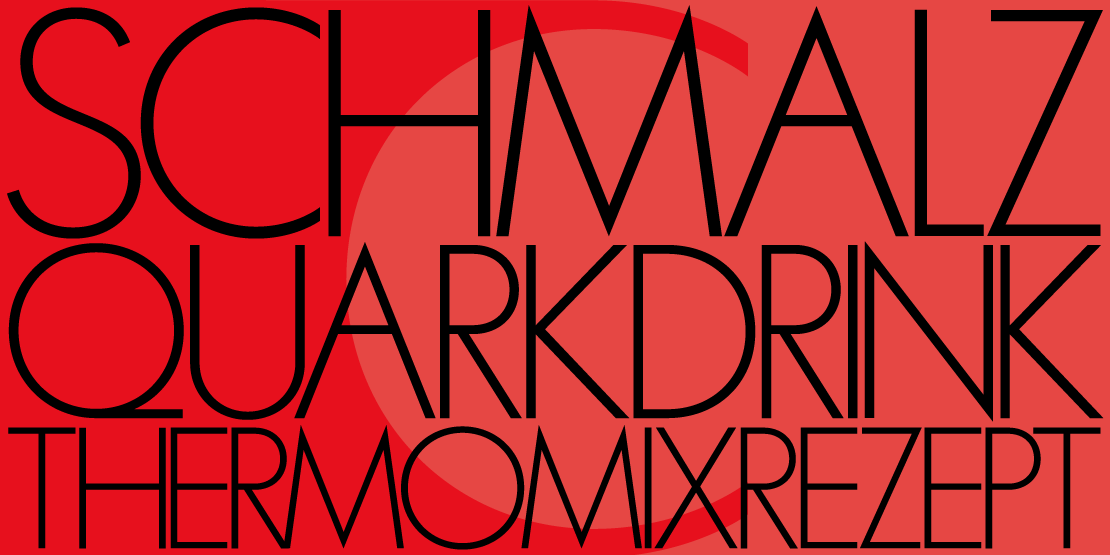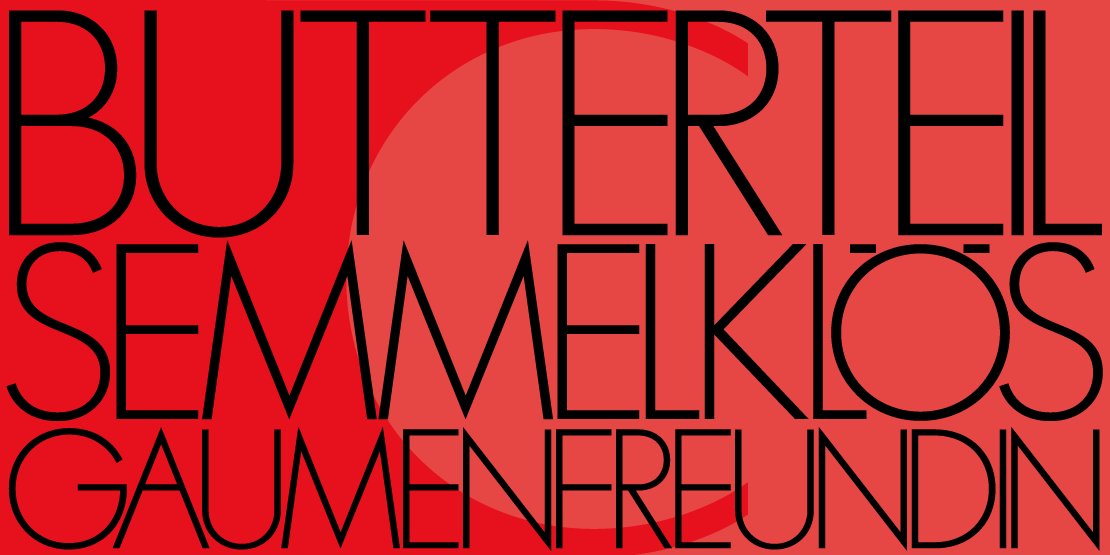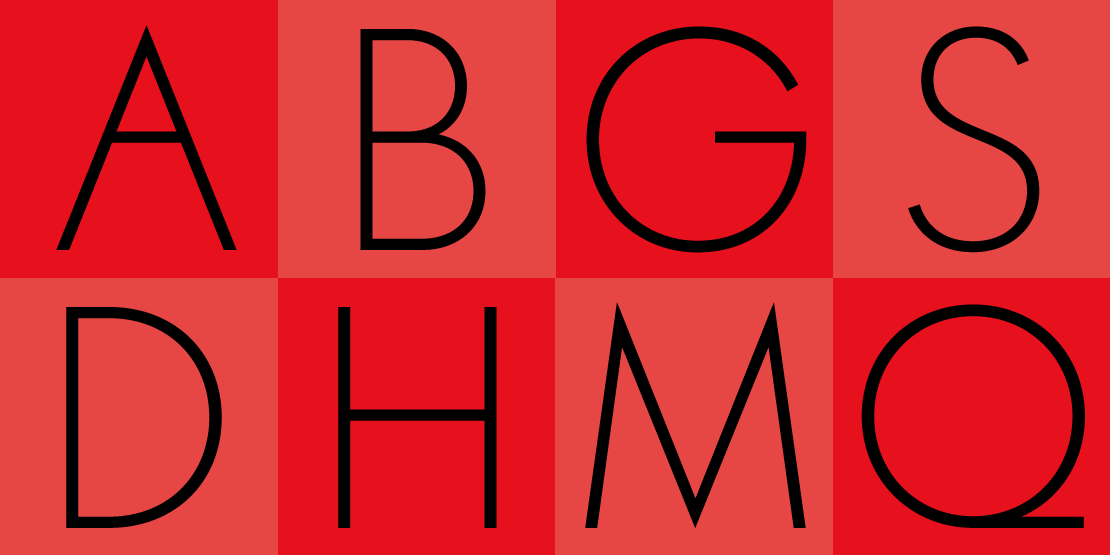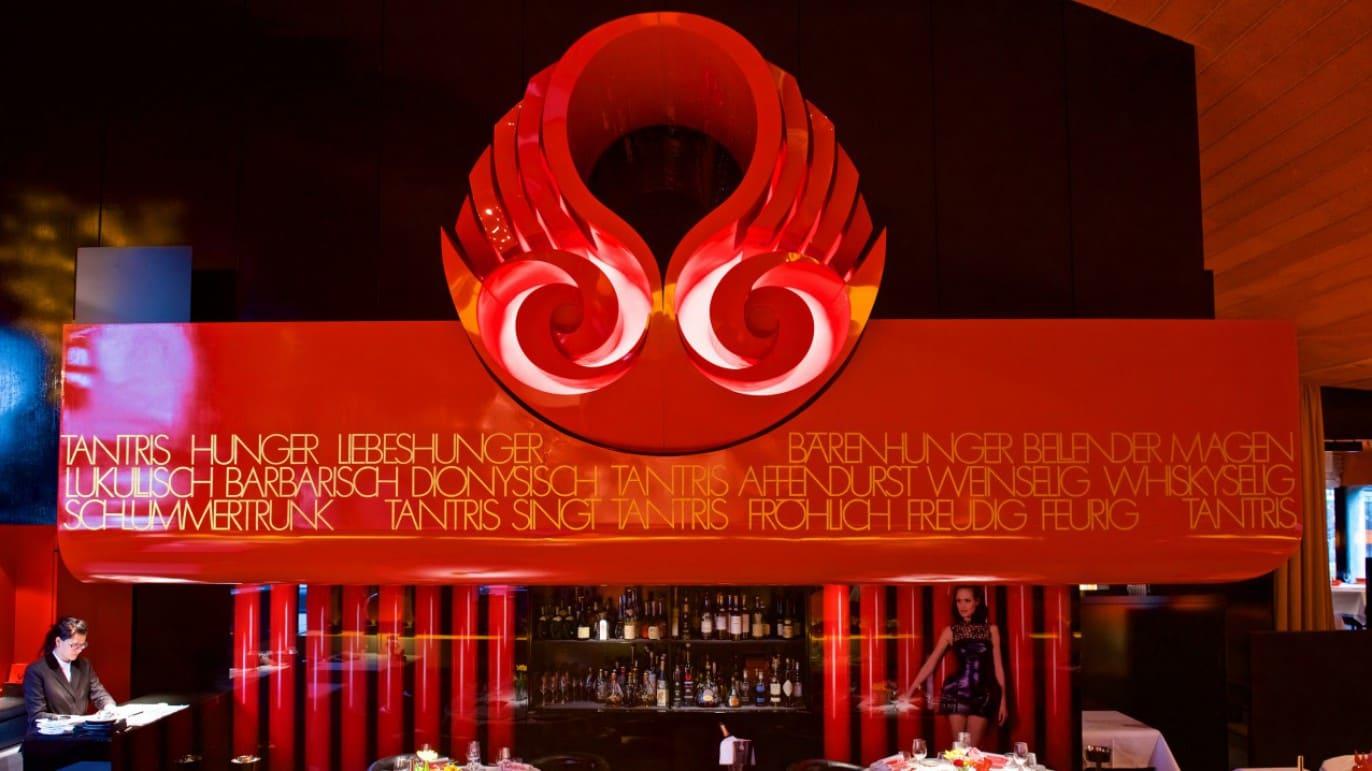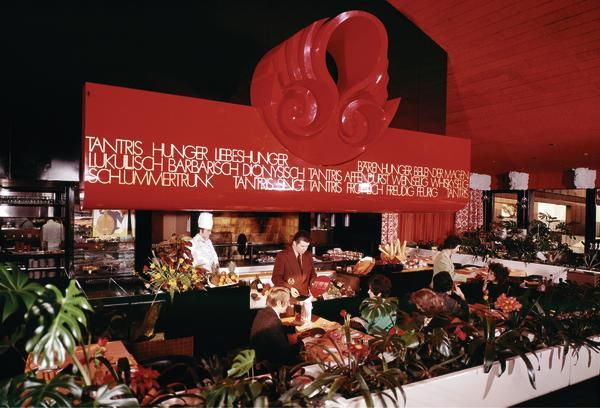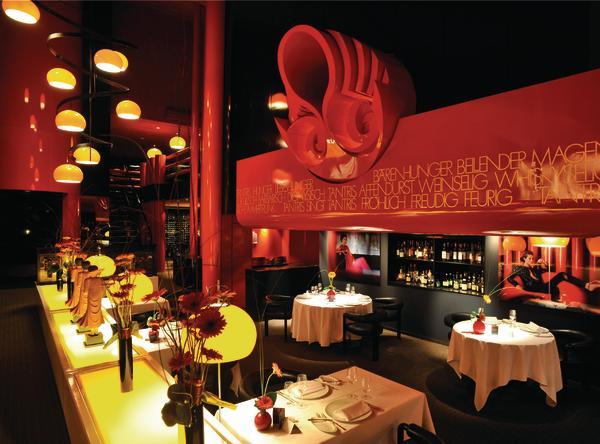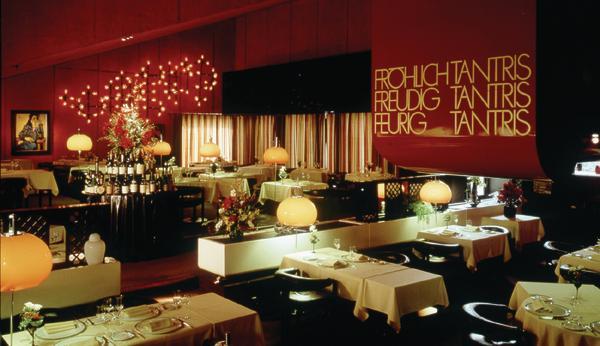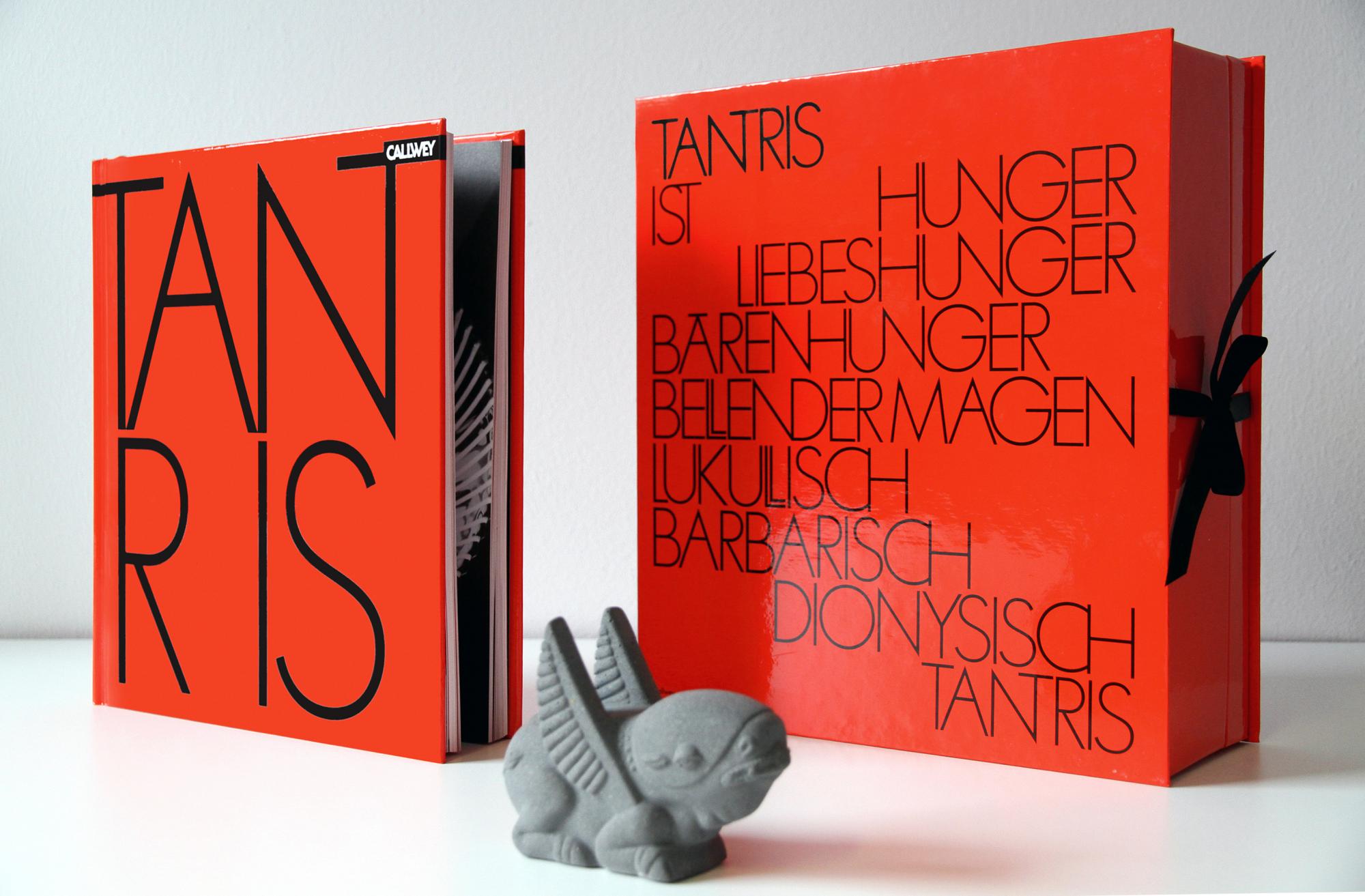
[Mitglied Inca…] Geschrieben April 28, 2015 Teilen Geschrieben April 28, 2015 Liebes Forum, kennt jemand den Font, der für das Logo des Restaurants "Tantris" in München verwendet worden ist? Website oben links: http://www.tantris.de/ Herzlichen Dank! Incandenza Link zu diesem Kommentar
[Mitglied catf…] Geschrieben April 28, 2015 Teilen Geschrieben April 28, 2015 Jemand? Ja, bestimmt der Gestalter des Logos, wenn dieser überhaupt einen Font verwendet hat, und diese 6 Buchstaben nicht komplett frei gestaltet hat. Und wer das gestaltet hat, das sollten die Inhaber ja auch wissen, Frag doch einfach mal da an, z.B. dass du dir von dem gleichen auch ein Logo gestalten lassen möchtest. 1 Link zu diesem Kommentar
[Mitglied Bern…] Geschrieben April 28, 2015 Teilen Geschrieben April 28, 2015 Nicht wirklich ähnlich, aber m.E. mit ähnlichen Assoziationen behaftet: https://www.behance.net/gallery/2625009/Ananda-Namaste-Free-Font mit durchgehender oberer Linie (hat die eigentlich einen Namen?). 1 Link zu diesem Kommentar
[Mitglied 3d3a…] Geschrieben April 29, 2015 Teilen Geschrieben April 29, 2015 … mit durchgehender oberer Linie (hat die eigentlich einen Namen?). Die heißt rekhā रेखा ('Linie') http://de.wikipedia.org/wiki/Devanagari Link zu diesem Kommentar
Beste Antwort [Mitglied Weys…] Geschrieben November 5, 2019 Beste Antwort Teilen Geschrieben November 5, 2019 Das Design des Münchner Gourmet-Restaurants Tantris ist legendär. Die Tatsache, dass es seit Eröffnung des Lokals 1971 bis heute kaum verändert wurde, ist mehr als bemerkenswert. Es stammt vom Architekturbüro Prof. Dr. Justus Dahinden. Die Hausschrift ist an die Futura angelehnt, weist aber – beispielsweise beim großen A – Unterschiede auf, die in Richtung Art Deco gehen. Die zahlreichen Ligaturen dürften von Herb Lubalin inspiriert sein, waren doch seine Arbeiten – insbesondere die Avantgarde – für diese Zeit stilprägend. Für ein Buchprojekt wurde Hubert Jocham 2014 beauftragt, ein Redesign der Schrift zu erstellen. Sie heisst Tantris SSANS. https://www.tantris.de/de/ https://www.hubertjocham.de/shop/type/display/TantrisSans/ Herzlichen Dank an Anita Riedl und Pascale Luise Kassel für die hilfreichen Auskünfte. 4 Link zu diesem Kommentar